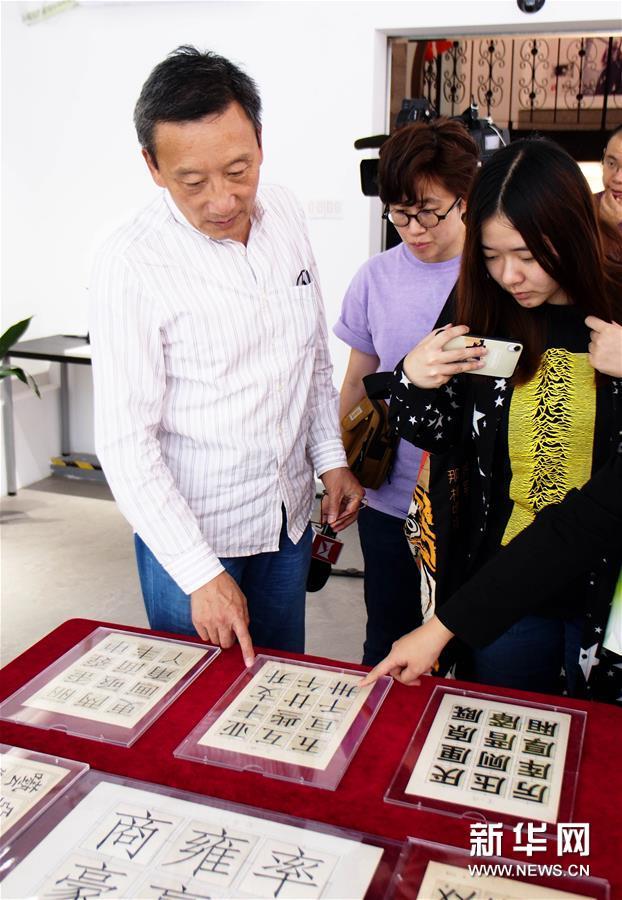
10月14日,非遗传承人原伟民在上海印刷字体展示馆里介绍标准印刷字体的创写过程。新华社记者 任珑 摄
新华社上海10月15日电(记者许晓青)14日,上海举行“现代汉字印刷字体发源地”命名及上海印刷字体展示馆揭牌仪式。
位于上海市新闸路1209弄60号的上海印刷字体展示馆,是现代汉字印刷字体发源地。新中国成立后,上海印刷技术研究所率先在此从事汉字印刷字体科研攻关。这座老洋房见证了当下广泛使用的宋体、黑体、仿宋体、楷体汉字印刷字体的原始创写过程。经过60多年的探索,在字形规范、字体创新、字库数字化建设上,上海印刷技术研究所已经形成了富有中国特色的汉字印刷字形技术标准,并具备专业化的检测能力。
2009年,经上海市人民政府批准,上海印刷技术研究所“汉字印刷字体书写技艺”项目,被列入第二批上海市非物质文化遗产名录。研究所现拥有数十名非遗传承人。
“今天,当我们打开电脑,经常使用的输入法所显示的‘宋体’,其实是当年研究所老一辈工作者创写的‘宋体二号’字体。”相关非遗技艺的第三代传承人原伟民介绍。